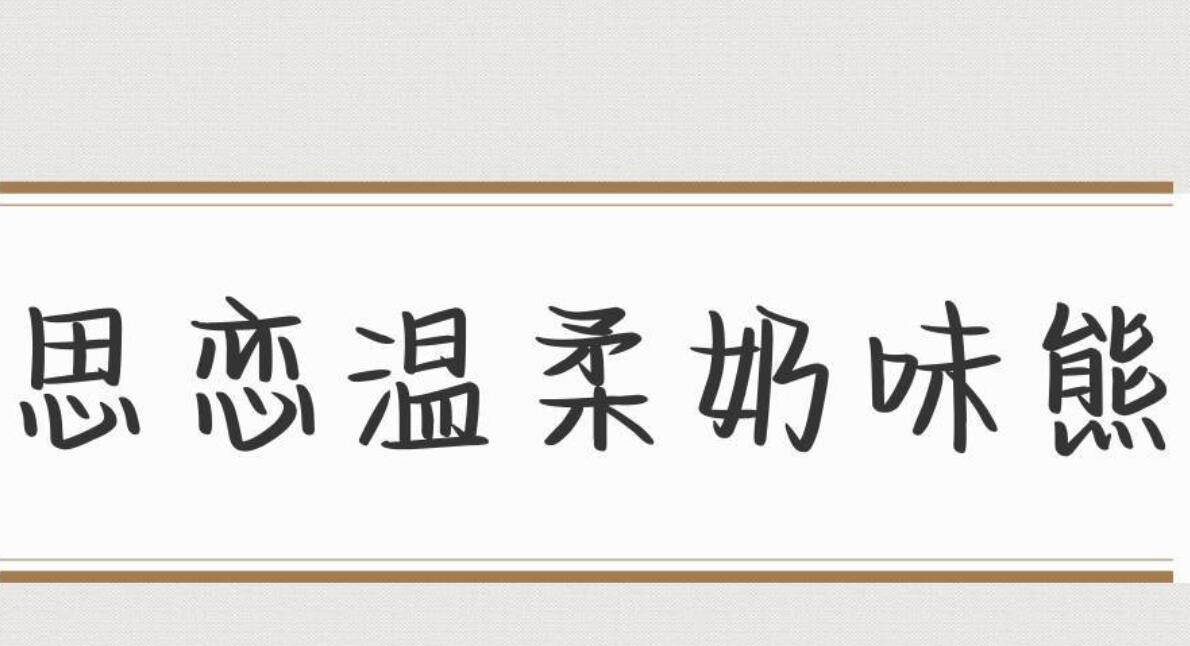
思戀溫柔奶味熊是文道字庫(kù)推出的一款非常不錯(cuò)的藝術(shù)字體,連貫字跡顯得干練而不凌亂,清新簡(jiǎn)明,具有很好的視覺感,適合應(yīng)用于藝術(shù)設(shè)計(jì)、平面宣傳設(shè)計(jì)、網(wǎng)頁(yè)設(shè)計(jì),書法字帖等領(lǐng)域,歡迎喜歡冬日限定草莓字體的朋友前來(lái)下載使用